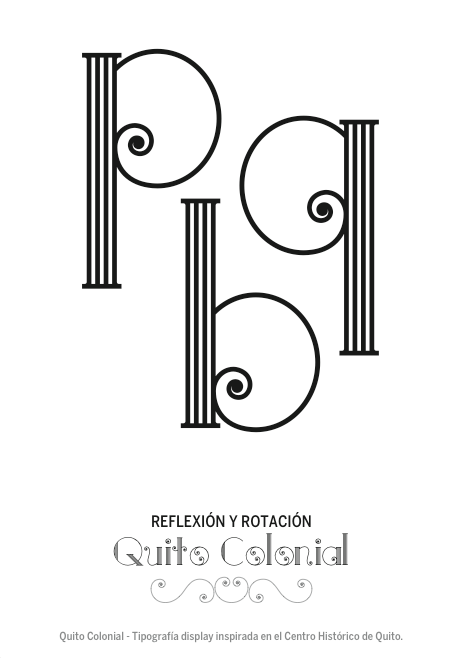
Font name: | Quito Colonial |
Author: | David Ortega |
Note by David Ortega | |
Esta tipografia esta inspirada en el Centro Histórico de la Ciudad de Quito, Ecuador, el concepto empleado es el uso de elementos arquitectónicos que se repiten en la mayoría de construcciones, estos son las columnas de estilo neoclásico y los balcones forjados en estilo art nouveau, mezclados para representar el estilo ecléctico que caracteriza este lugar. |